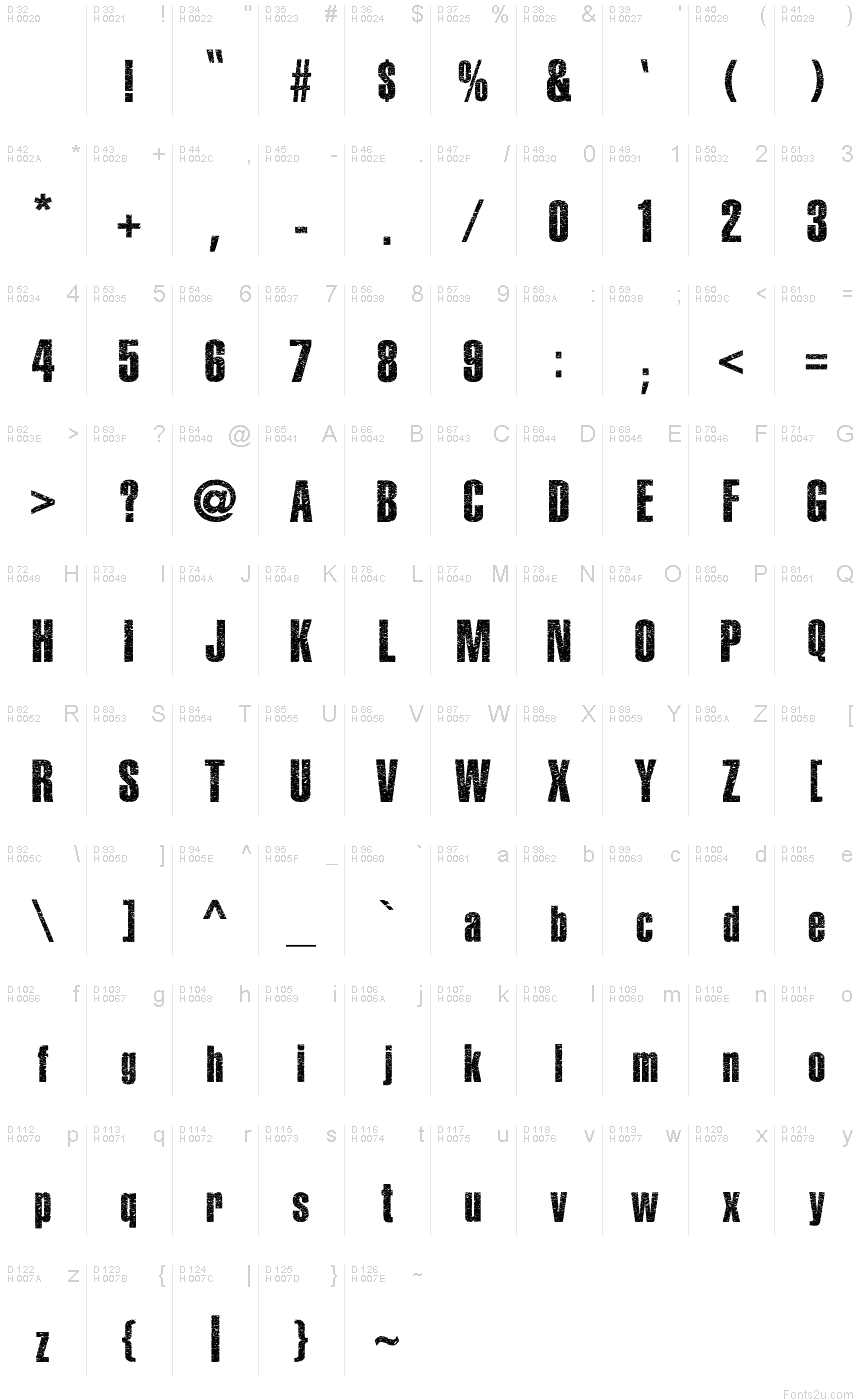
Momento Mori, die kostenlose, erodierte Display-Schrift von John Flickinger, setzt auf eine abgenutzte Letterpress-Ästhetik. Mit ihren rauen, verwitterten Kanten und der kräftigen Textur, die sich in jeden Strich frisst, wirken die Buchstaben eher von der Zeit gezeichnet als bloß verziert. Das verleiht der Schrift eine ungeschliffene, düstere Präsenz, die rau und menschlich wirkt.
Sie eignet sich hervorragend für Poster, Album-Cover, Horror-Designs, Zines und Titelkarten, bei denen eine kostenlose Schrift mit echtem Abrieb die Stimmung maßgeblich prägt. Verwenden Sie sie für kurze Überschriften, dramatische Cover-Lines oder eine einzelne übergroße Initiale, wenn die vernarbte Textur mehr Charakter vermitteln soll als reine Ornamentik.